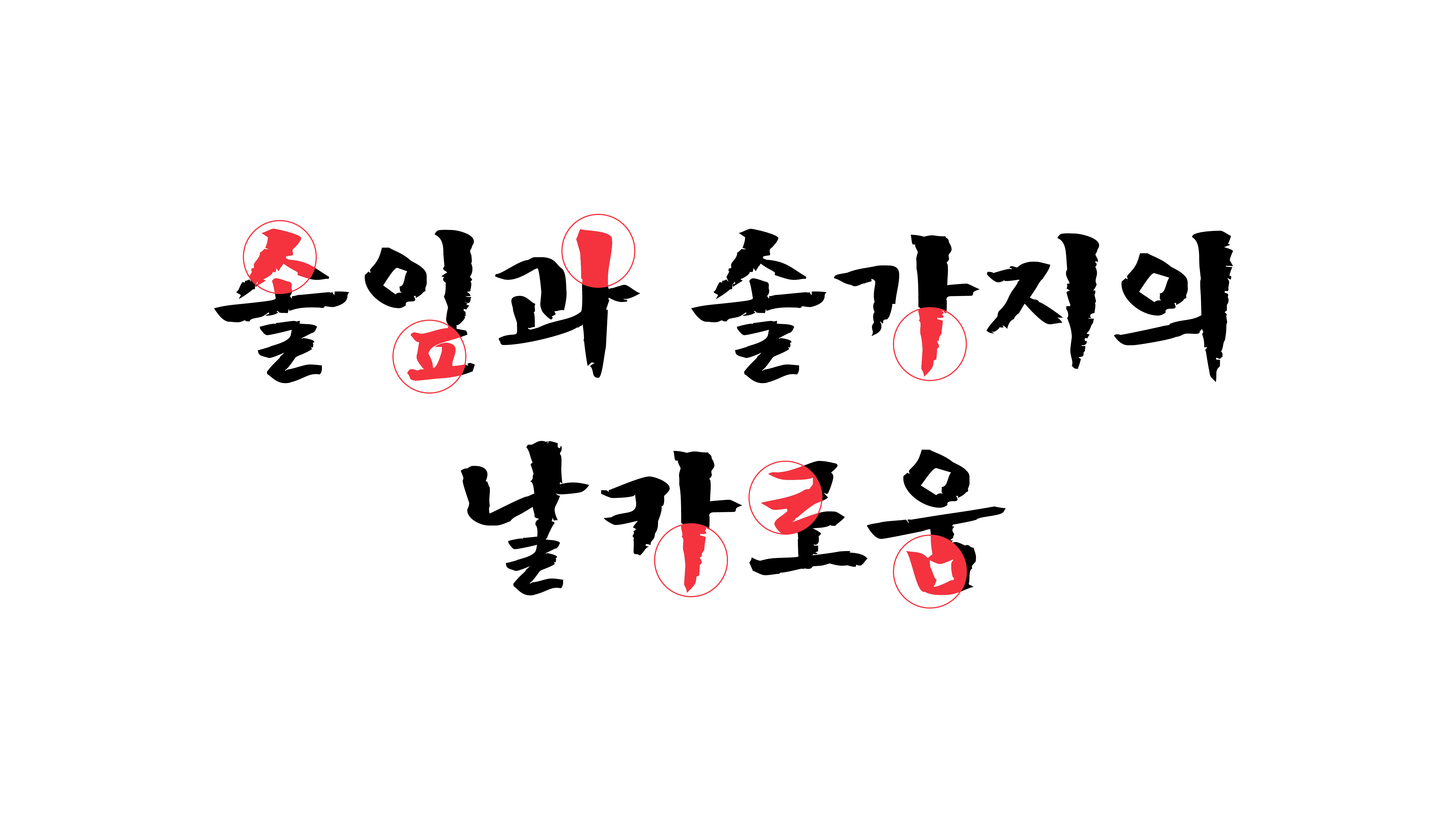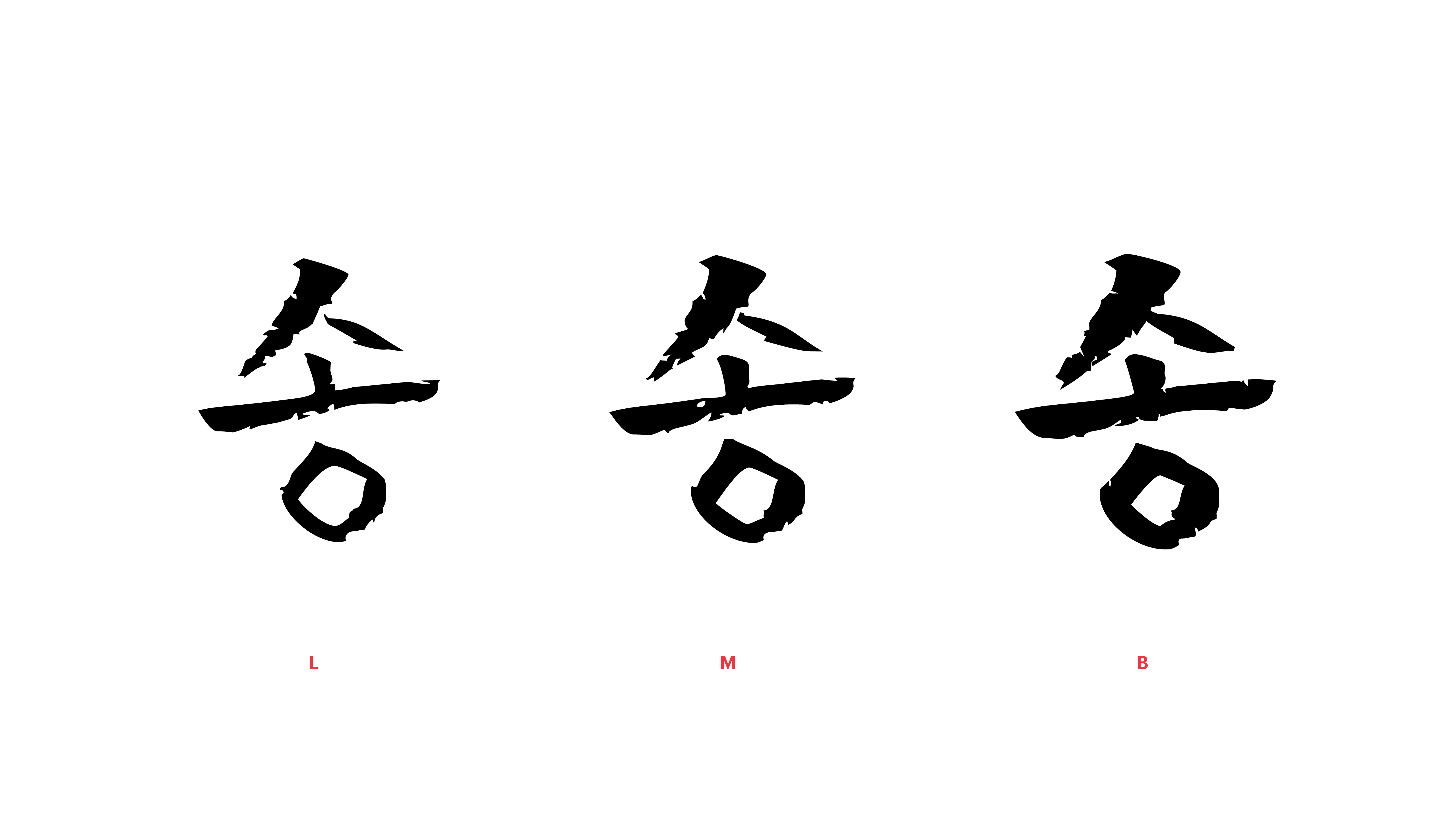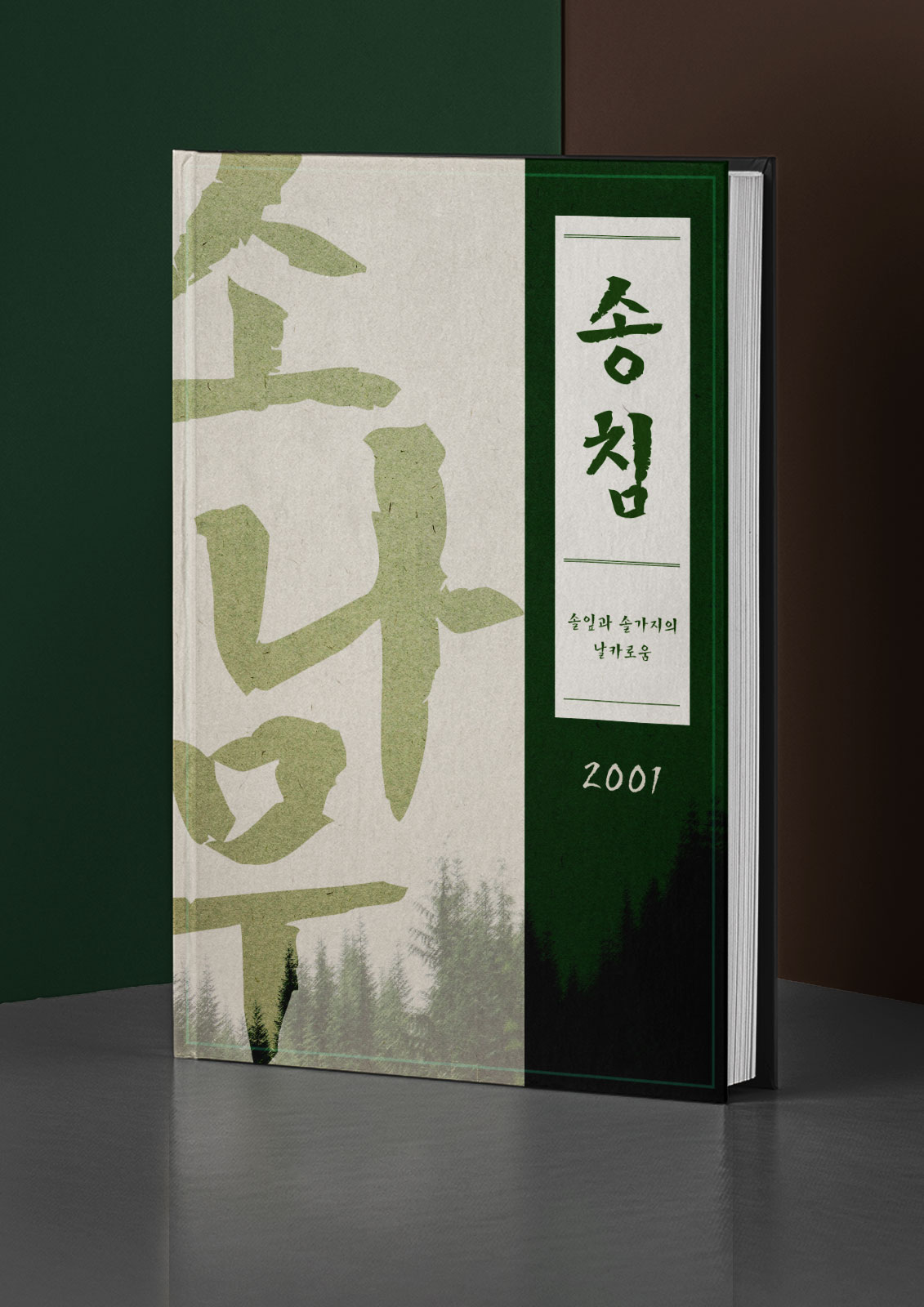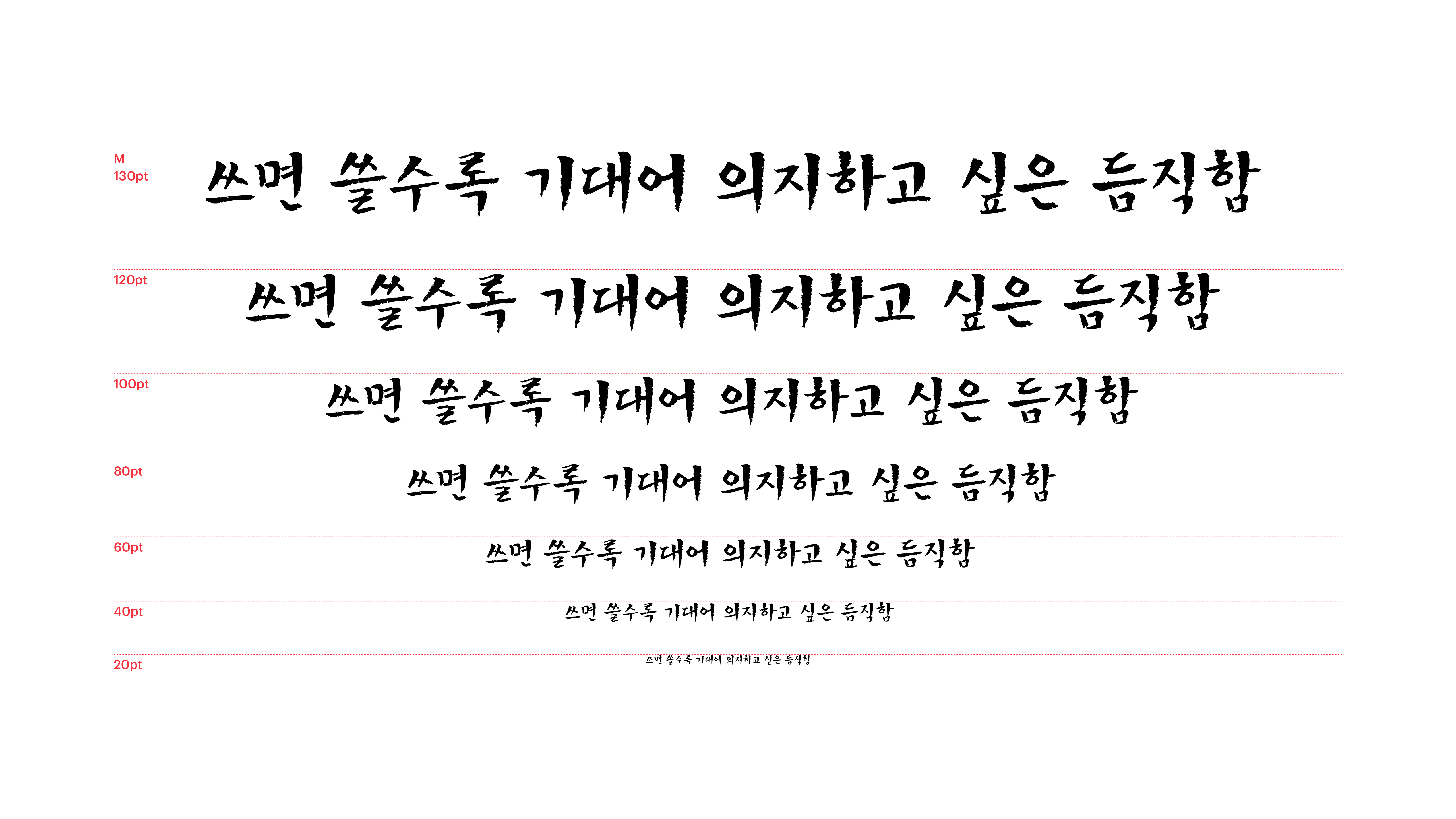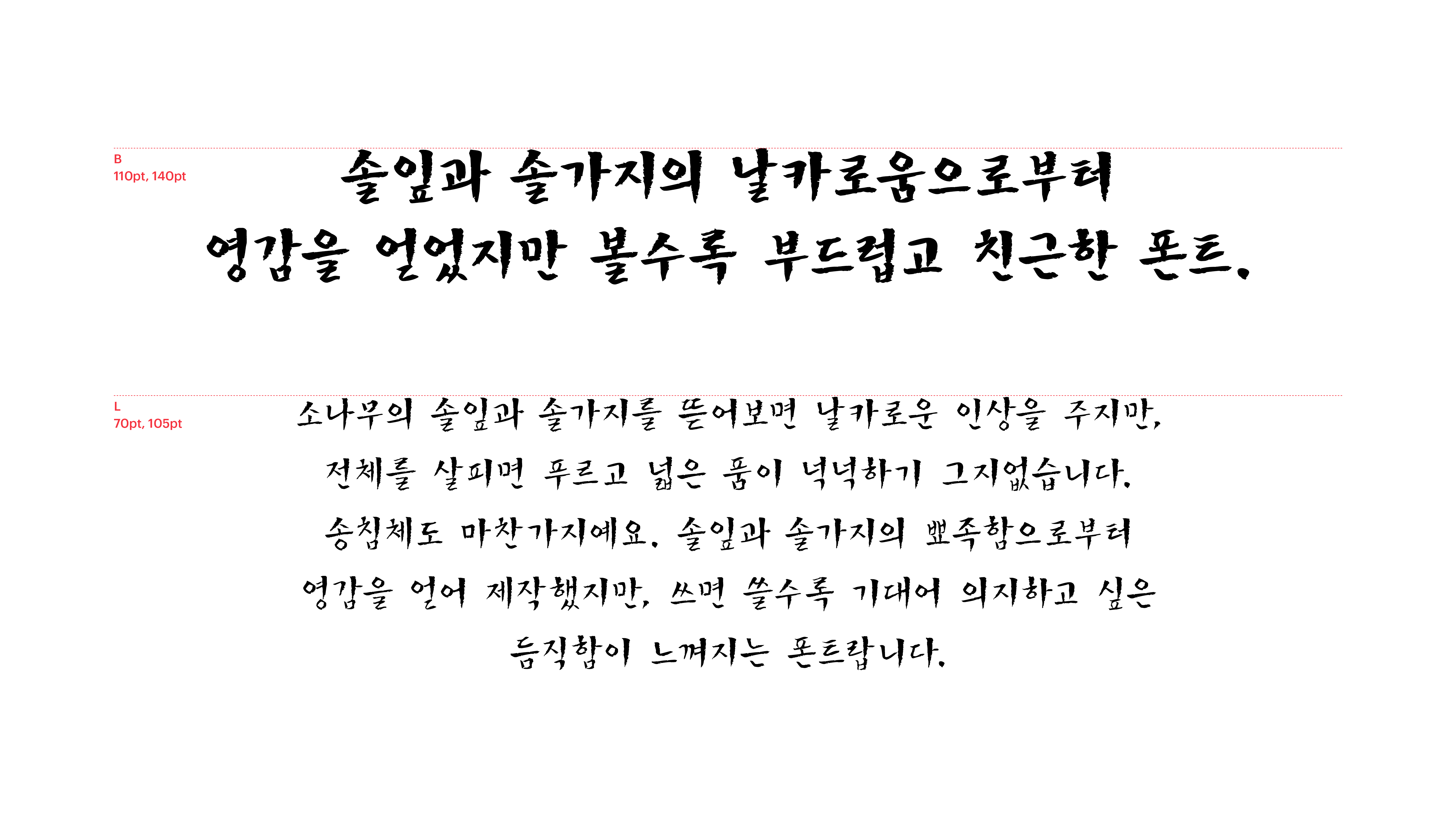
송침
Yoon 송침
소나무의 솔잎과 솔가지를 뜯어 보면 날카로운 인상을 주지만, 전체를 보면 푸르고 넓은 품이 넉넉하기 그지없습니다. 송침체도 마찬가지예요. 솔잎과 솔가지의 뾰족함으로부터 영감을 얻어 제작했지만, 쓰면 쓸수록 기대어 의지하고 싶은 듬직함이 느껴지는 폰트랍니다.